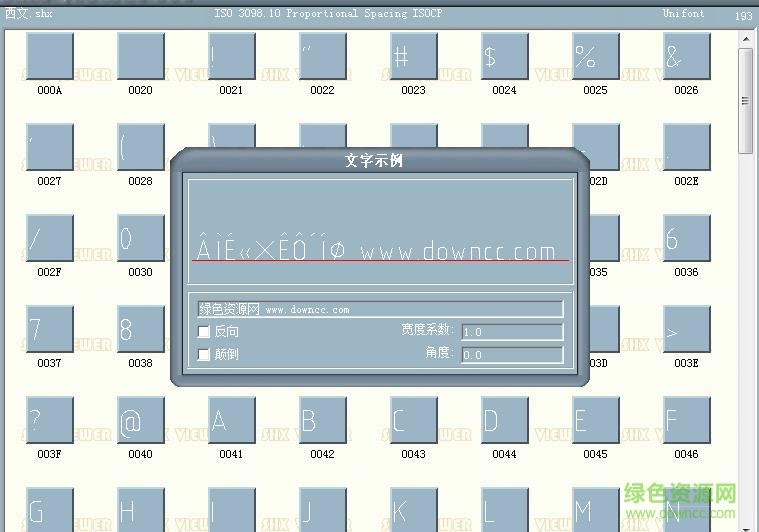
正體西文.shx字體通過(guò)不斷演化發(fā)展,成了了如今在各行各業(yè)中廣為流行使用的字體樣式,讓你能夠完成眾多的圖紙制作效果,獲得完美的工業(yè)制圖圖紙!
正體西文.shx不局限與字體輸入,還能輸入眾多的符號(hào),阿拉伯?dāng)?shù)字,其內(nèi)的字體樣式十分優(yōu)美,讓你在使用與觀看的過(guò)程中都能夠感受到不同的精神享受!